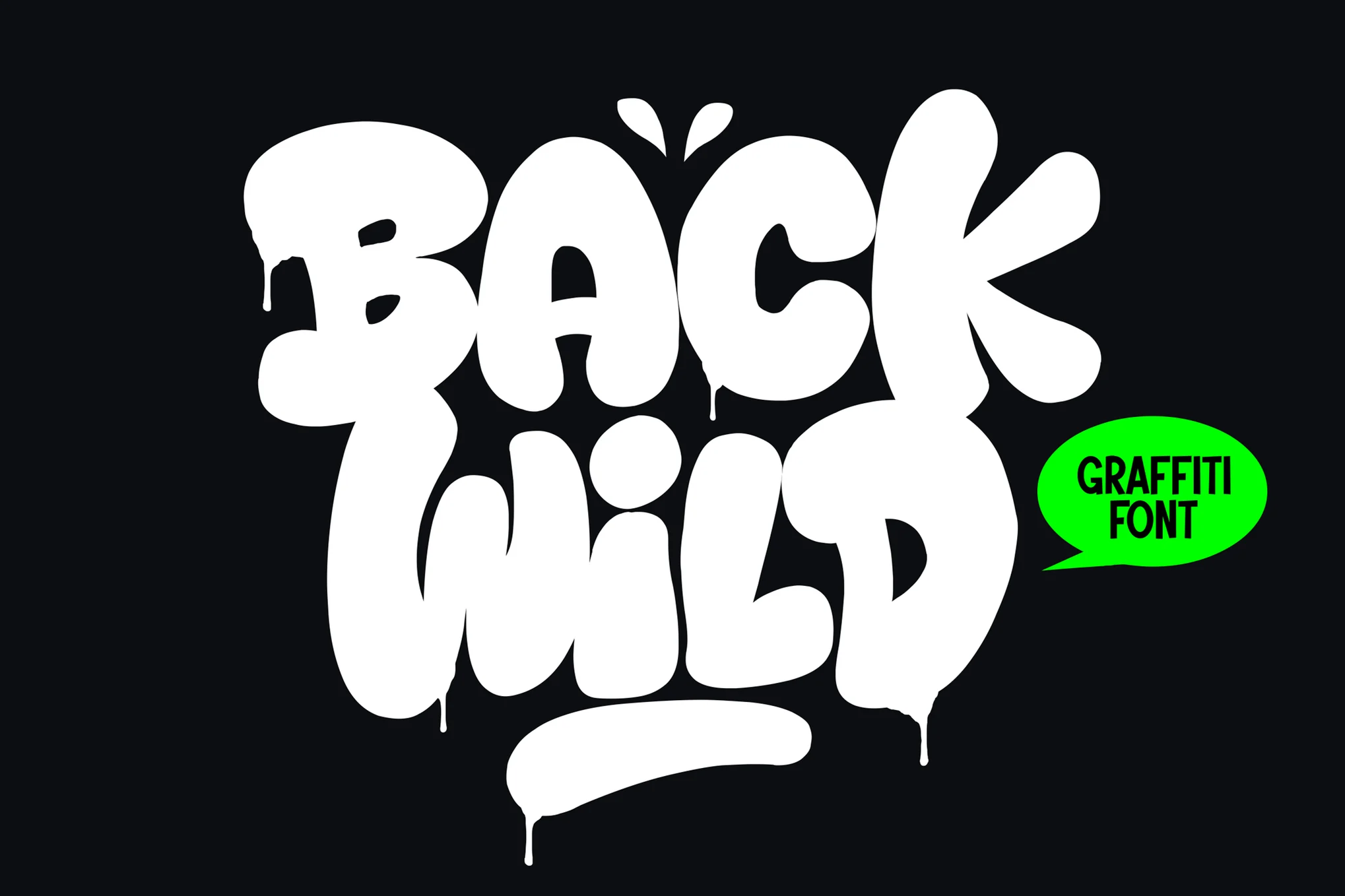
🎨 Back Wild – فونت گرافیتی پرانرژی و خلاقانه
Back Wild فقط یک فونت نیست؛ بلکه یک بازی شهری از خلاقیت است! این فونت گرافیتی پرجنبوجوش، همراه با Swashهای اضافی، به طراحیهای شما هیجان و شور و نشاط خیابانی میبخشد.
✨ ویژگیهای برجستهی Back Wild
✅ سبک گرافیتی پویا و منحصربهفرد
- حروف آزاد و سرکش با روحیهی خیابانی
- مناسب برای پوسترها، طراحیهای استریتاستایل، تیزرها و پروژههای پرانرژی
✅ ویژگیهای فنی
- دارای کاراکترهای استاندارد و علائم نگارشی
- پشتیبانی از چندین زبان
💡 چرا Back Wild؟
✔ ایدهآل برای طراحی خیابانی، موسیقی، استایل هیپهاپ و آثار جسورانه
✔ ایجاد حس آزادی و انرژی در تایپوگرافی
✔ فونتی خاص برای پروژههای گرافیکی با تم شهری و معاصر
🔥 با Back Wild، طراحیهای خود را به سطح جدیدی از خلاقیت و شور و هیجان برسانید! 🎨